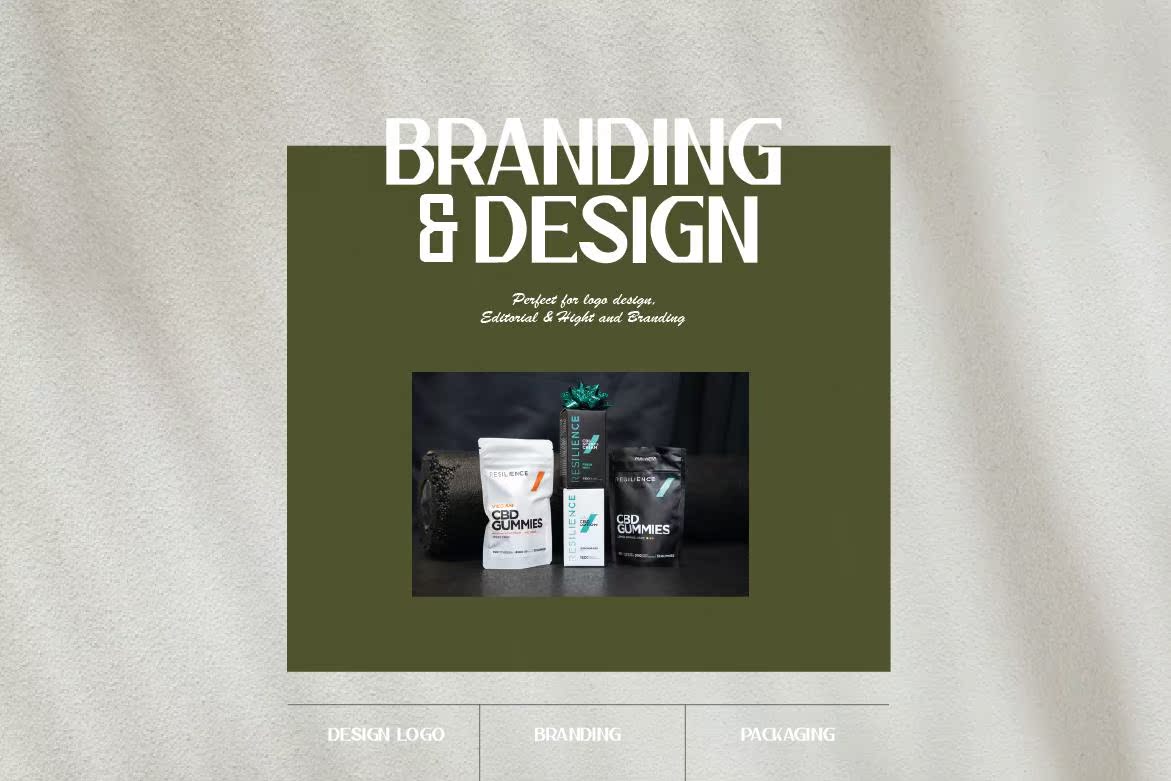
Jugfulisanalegant和CleanSansserifont。它的存储空间仅限于家庭设计,用于强大、经典的展示。甘特图完美,适用于任何品牌、徽标、杂志、视频、婚礼、报价、印刷、产品包装、网站、服装设计,以及更多的Jugfulisanalegant和CleanSserifont。它的存储空间仅限于家庭设计,用于强大,经典解析。甘特图完美,适用于任何品牌、徽标、杂志、视频、婚礼、报价、印刷品、产品包装、网站、服装设计等